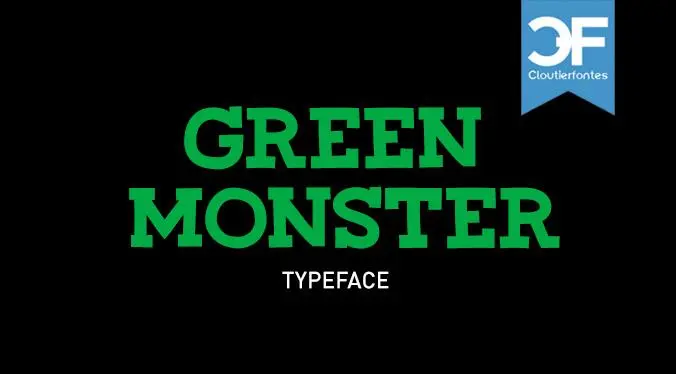
A CF Green Monster é uma slab serif fonte com um visual elegante e versátil, perfeita para adicionar profundidade a qualquer projeto. Seu design geométrico e arredondado proporciona um estilo minimalista que se adapta à variedade de aplicações gráficas: desde logos e materiais promocionais até logotipos em papel e site web. Como uma fonte slab serif, ela é conhecida por suas curvas levemente contornadas, deixando-a suavemente elegante mesmo sob condições digitais. O designer, Hamilton, criou uma fonte que se destaca não apenas pela beleza visual, mas também pela sua versatilidade. Seu trabalho é especialmente valorizado para aqueles buscando uma fonte única e atraente, capaz de capturar o interesse do público visando seu uso em um contexto pessoal ou comercial. A fonte oferece tanto um estilo moderno quanto um tom clássico que pode ser facilmente adaptado à sua necessidade de design. Se você está procurando por uma fonte de slab serif para seus projetos, mas quer garantir a disponibilidade e licenciamento, considere a CF Green Monster. Seu designer, Hamilton, oferece opções para uso pessoal gratuito ou licenças comerciais mais extensas conforme seu nível de utilização. Escolha a fonte que se encaixa melhor no seu projeto e sinta-se à vontade para explorar suas capacidades impecáveis e estilo único.